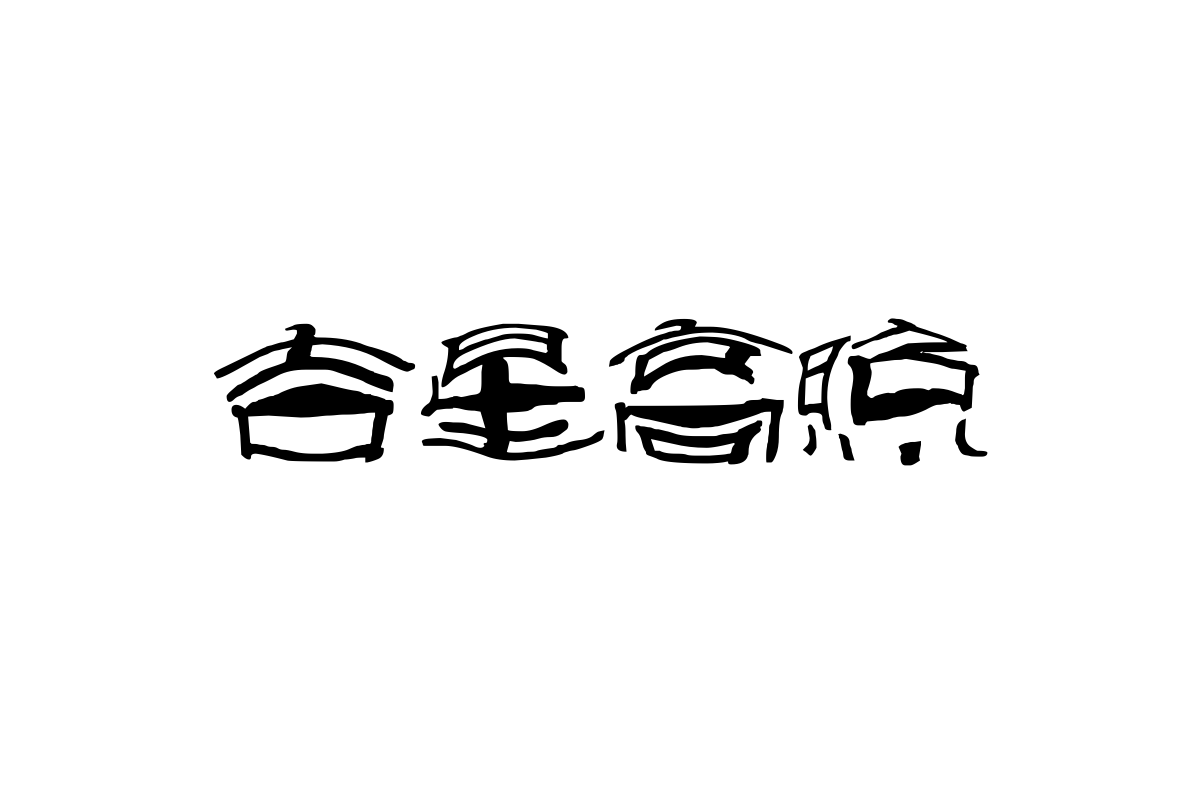
段宁球体是一款创意字体,由设计师段宁创作。这款字体具有独特的设计风格和特点,适合用于各种场景和品牌宣传。它的笔画流畅自然,线条简洁明快,给人一种轻松愉悦的感觉。同时,字体的字形结构也具有一定的规律性和美感,使得整体视觉效果更加和谐统一。
段宁球体是一款适用于广告、标识、海报等场景的字体。它能够很好地传达出品牌的个性和风格,吸引观众的注意力。此外,这款字体还具有较强的可读性,适用于各种文字内容的创作和排版设计。